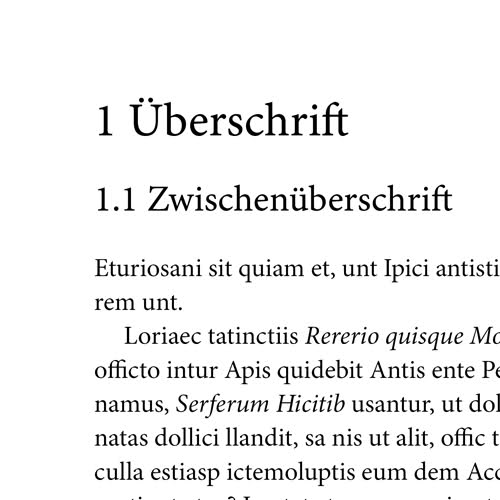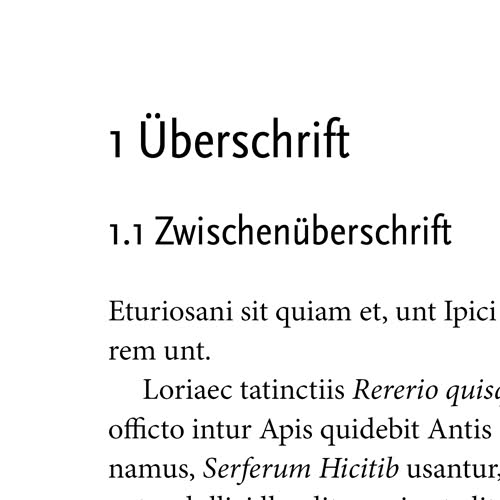
Sans Serif zur Minion
als Serif benutze ich ausschließlich die Minion. Bisher habe ich ganz klassisch die Myriad als Sans dazu genommen. Nur muss ich zugeben, dass mir die Myriad nicht sondernlich gefällt.
Gerade bei Arbeitsblättern (z.B. mit Text in Spalten, Listenaufzählungen, Quellenkästen oder Gedichten, aber auch teilweise mit kürzeren Textabschnitten bis ca. 1/2 Seite) würde ich gerne eine andere Sans Serif benutzen. Diese Blätter sind bisher durchgehend in Myriad gestaltet.
Eine Alternative sollte möglichst zur Minion passen, da ich in "Nur-Text"-Dokumenten die Minion benutze und bisher die Myriad als Überschrift/Hervorhebung einsetze. Quasi als persönliche Cooperate-Identity :D
Meine Versuche gingen über Syntax (gut für längere Texte, aber zu wenig Absetzung von der Serif-Schrift), Frutiger (hat leider nur eine viel zu dicke Bold,sticht überproportional hervor,in Spalten zu weitläufig), Futura (längere Texte waren irgendwie anstrengend) ....
Wie sieht es mit der Gill Sans aus? Diese schlägt sich bei meinen Anforderungen recht gut. Nur: passt diese auch gut zur Minion. Oder gibt es bessere Alternativen?
Ich habe ja in letzter Zeit viel Minion/CamingoDos Pro semicondensed semibold benutzt. Mir persönlich gefällt das nach wie vor recht gut.
CamingoDos condensed
CamingoDos semicondensed
Wie wäre es ansonsten mit der Tungsten von Hoefler & Frere Jones? Oder, wenn es nicht condensed sein soll, die Karmina Sans von typetogether?
Die Hypatia habe ich gleich ausprobiert. Sie hat leider die gleichen "Probleme" wie die Frutiger. Die fette Auszeichnung ist für meinen Einsatzbereich einfach zu stark. Ansonsten wäre sie brauchbar.
Auf die CamingoDos habe ich leider keinen Zugriff. Wäre aber eine Überlegung wert. Vielleicht gönne ich mir einige Schnitte zu Weihnachten. (bin ja nur Laie).
Bin gerade am rumprobieren... Und nun habe ich eine allgemeine Frage:
Kann ich auch ganz auf eine serifenlose Schrift verzichten? Gibt es da eine Regel?
Gerade bei längeren, durchgehenden Texten finde ich dies eine ganz gute Wahl. Gerade da Minion ja auch über optische Größen verfügt.
Wie sieht es aber bei kürzeren Texten aus? Kann man hier auch eine Serifenschrift wählen, und eine gute Lesbarkeit erreichen? Ist das auch bei Aufzählungslisten ansprechend und lesbar? Hier bin ich mir nicht sicher. Gibt es da eine Regel oder von eurer Seite Erfahrungswerte?
In schmaleren Spalten bin ich gerade von Minion Condensed angetan. Bin ich bis jetzt garnicht drauf gekommen. Bei einer 2 spaltigen Tabelle auf einem DinA4 Blatt hochkant, erscheint es mir angenehmer, als die Myriad oder Frutiger.
Ansonsten würde ich einfach für alles in der Minion und ihren verschiedenen Schnitten setzen. Oder ist das zu langweilig?
Also, grundsätzlich benötigst Du selbstverständlich keine Serifenlose in Kombination zu einer Serifenschrift; eine Schrift in einem Dokument durchgängig zu verwenden sieht sehr klassisch aus, immer eine Schöne Sache™:
Wenn Du für die Überschriften eine Serfienlose hernimmst, wird das Ganze etwas moderner:
Weiterhin eröffnen sich neue Möglichkeiten; auf einem Arbeitsblatt könntest Du beispielsweise die Aufgabenstellungen in der Serifenlosen setzen, dann bleibt Dir die Serifenschrift ganz für die reinen Daten, und vielleicht in kleiner für Randnotizen und dergleichen ...
Möglichkeiten gibts einige, aber auf die Serifenlose zu verzichten ist keineswegs falsch :D
Falsch ist in gewisser Beziehung sowieso der verkehrte Ausdruck. Es geht hier ja in erster Linie darum, daß sich die Überschriften deutlich vom Fließtext abheben. Das erreicht man ganz allgemein mit Kontrast. Das kann der Weißraum sein, oder eine andere Schrift, eine andere Farbe, Versalsatz, Kapitälchen etc. Weiterhin müssen die Ebenen sofort und eindeutig identifizierbar sein. Bei dem Beispiel von Minimalist wird das durch die Benummerung erledigt und muß daher bei der Gestaltung nur eine untergeordnete Rolle spielen. Wenn man hingegen, so wie ich, die Benummerung als völlig überflüssig erachtet, dann muß man mehr Zeit darauf verwenden, die Hierarchie der Ebenen eindeutig zu klären.
Beispiele dazu findest Du in jedem Buch. Spontan fällt mir die die Diplomarbeit von Gerrit van Aaken dazu ein. Der benutzt eine andere Schrift, Schriftgröße, farbliche Abhebung und Linien-Elemente – trotzdem bleibt es für mich sehr stimmig.
In meiner eigenen Dissertation verwende ich nur die Minion; die Myriad kommt nur in Tabellenüberschriften und Bildunterschriften zum Einsatz. Auch wenn ich das heute vielleicht anders lösen würde: es funktioniert nicht schlecht. Wenn Du aber beide Dokumente vergleichst wird sofort deutlich, wie sehr sich der erste Eindruck unterscheidet.
Bei dem Beispiel von Minimalist wird das durch die Benummerung erledigt und muß daher bei der Gestaltung nur eine untergeordnete Rolle spielen. Wenn man hingegen, so wie ich, die Benummerung als völlig überflüssig erachtet, dann muß man mehr Zeit darauf verwenden, die Hierarchie der Ebenen eindeutig zu klären.
ein paar Mal habe ich die Kombination mit der Franklin Gothic (Condensed) gesehen. Ja nach Version scheint das halbwegs zu passen. Allerdings war IIRC die ITC-Franklin-Gothic bisschen unpraktisch wegen der großen Strichdickenunterschiede zwischen der Regular und der Bold. Da sollte man statt der Bold die DemiBold nehmen.
Ps: Das mit den Condensed Schnitten und der DemiBold statt Bold sollte auch auf die Frutiger übertragbar sein. Hast Du schon in diese Richtung probiert?